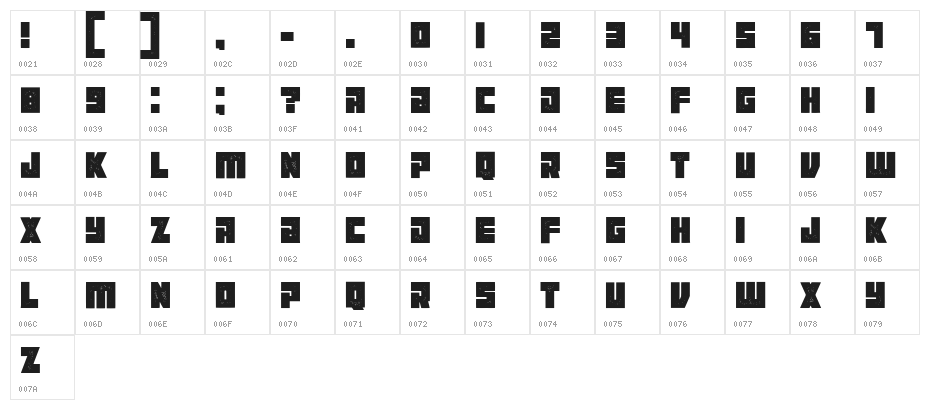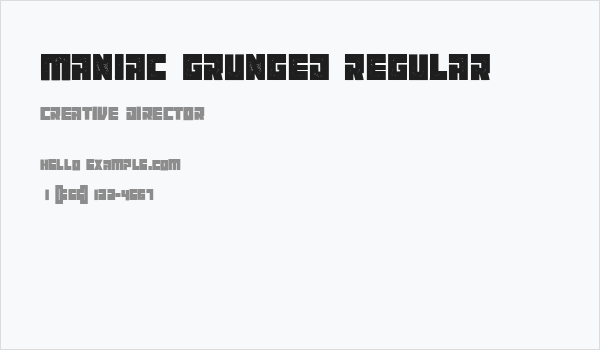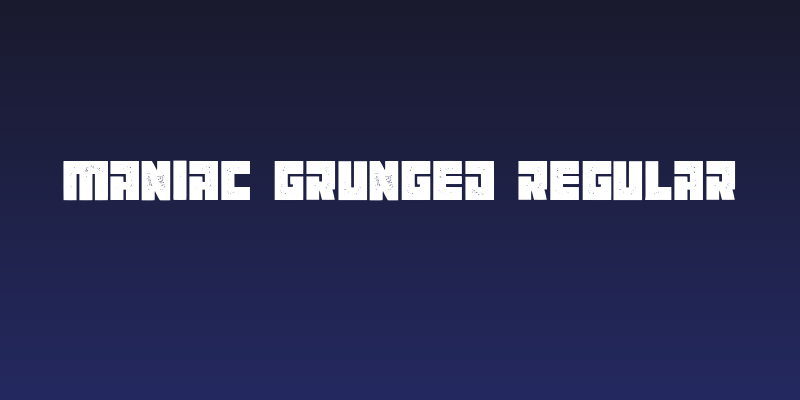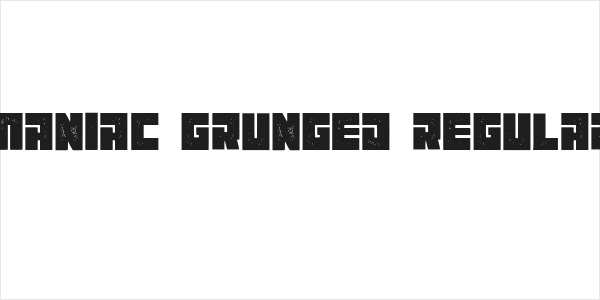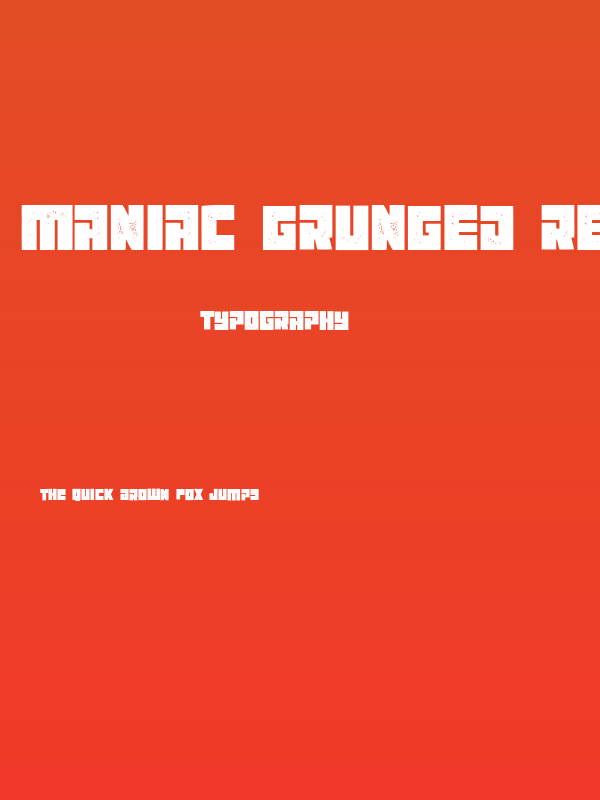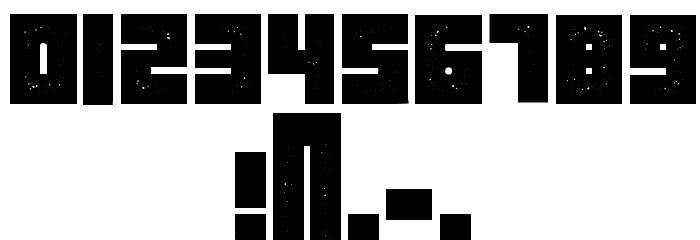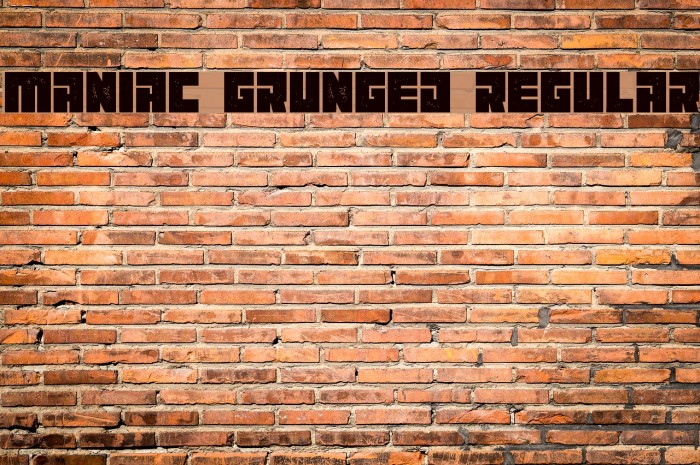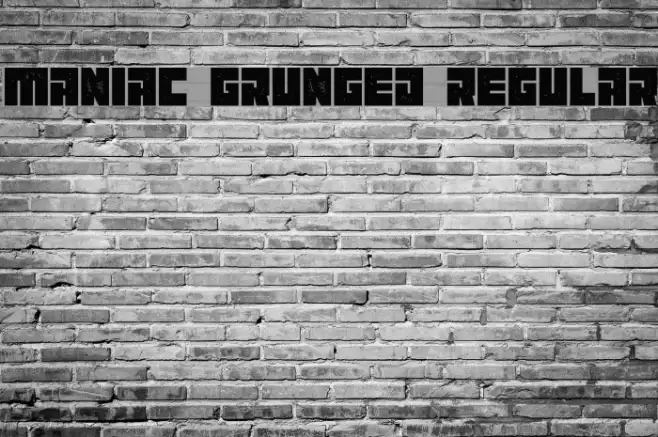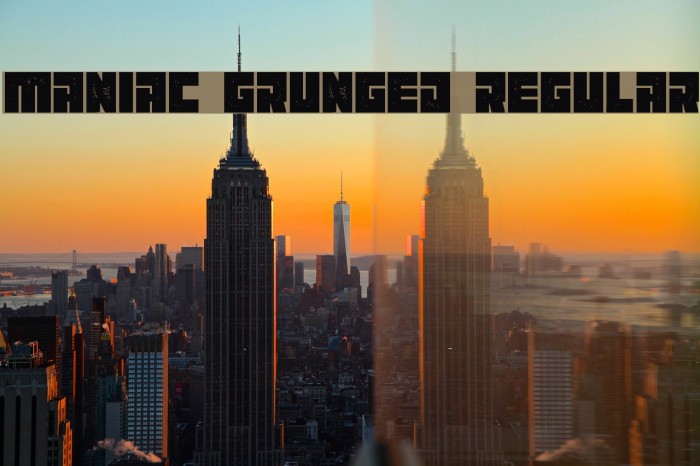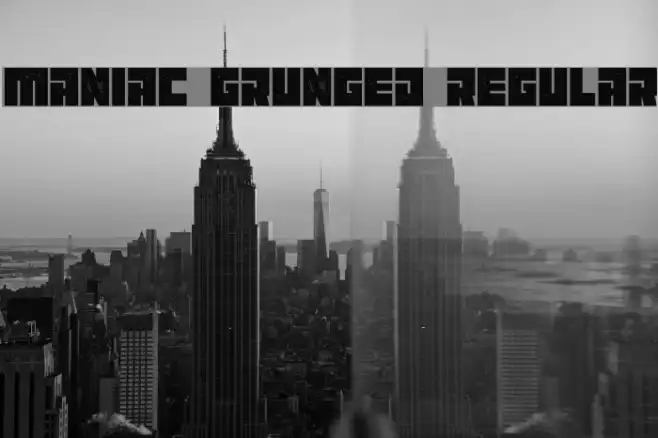
Maniac Grunged Regular Font
| Estilo general | Grunge, Urban, Edgy |
| Proyectos propuestos | Ideal for music album covers, posters, urban-themed designs, and branding that requires a strong, edgy look. |